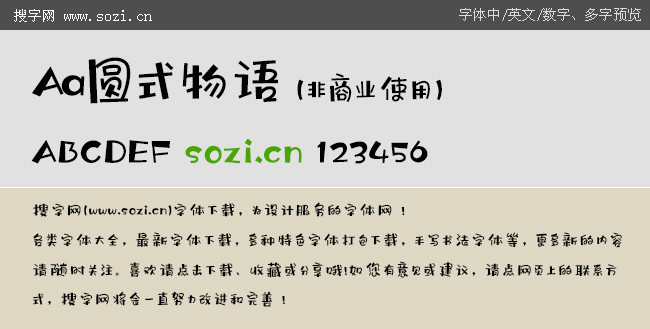
Aa圓式物語
搜字網(wǎng)給大家提供一款Aa圓式物語(非商業(yè)使用)中文字體下載,該字體是一款手寫風格的卡通字體,字體筆觸適中,圓潤可愛,具有很好的視覺感,適用于平面宣傳設計、網(wǎng)頁設計、海報設計等應用(此字體為個人非商用版,商用可以聯(lián)系QQ:1006760504)。